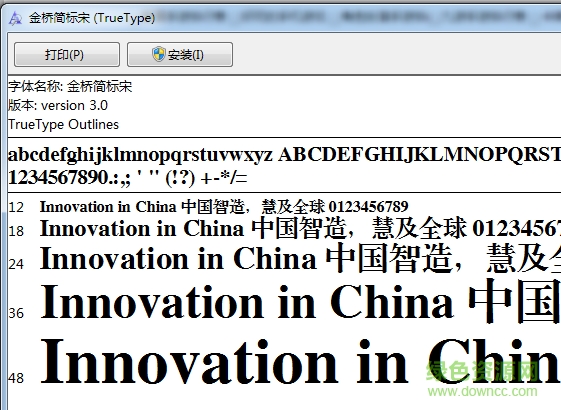
文字是書面的語言,它以符號的形式使語言插上了翅膀,得以超越時空,使上溯幾千年的先民與不能謀面的后代成為忘年神交之友。而印刷的誕生又使文字成為信息傳遞的最主要的渠道與載體。那么作為信息載體的印刷字體就不能像以往個體書寫行為那樣隨意了,從此,字體設(shè)計就成為了現(xiàn)實的需要。所以,“實用”就成為字體設(shè)計的首要目的。這說明字體設(shè)計是視覺傳達的重要手段之一,是運用裝飾手法加強和美化文字的一種創(chuàng)造性的書寫藝術(shù),亦即實用美術(shù)設(shè)計活動。同時也說明了字體設(shè)計活動不是同文字與生俱來的,印刷術(shù)的產(chǎn)生才使設(shè)計活動成為可能。其設(shè)計的根本目的不在于造字,特別是漢字的字體設(shè)計活動更不是要在傳統(tǒng)的篆、隸、楷、草、行等結(jié)字體系之外另創(chuàng)異體。其本意旨在初步了解、熟悉并運用現(xiàn)代美術(shù)字體,進而在以楷體為“母體”的基礎(chǔ)之上,在字體的外形、筆畫及局部結(jié)構(gòu)上進行某些裝飾、美化、創(chuàng)意變形等藝術(shù)處理,以便創(chuàng)造出更加貼近內(nèi)容,更能切合語境的具有個性化藝術(shù)風格及時代氣息的活潑生動的書寫形式來。凡符合這個目的,就能產(chǎn)生出色的設(shè)計作品,而違背了這個目的,就會使設(shè)計活動走上歧路。